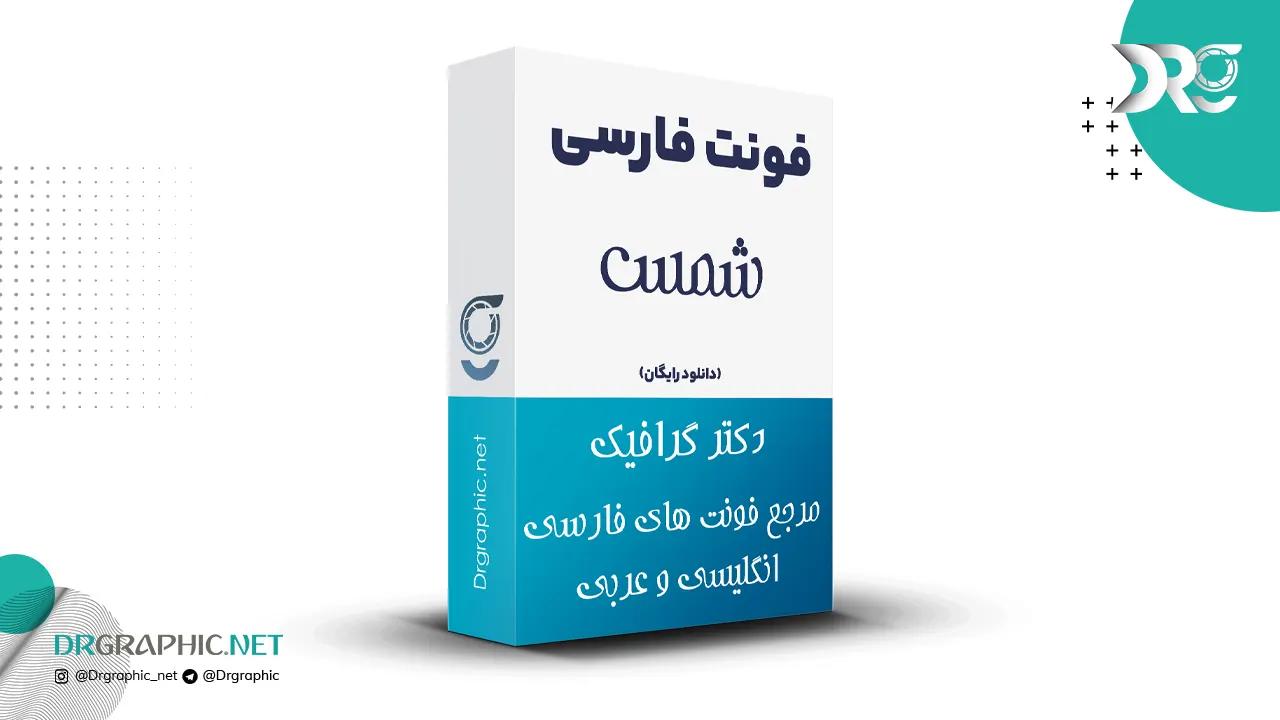
دانلود فونت فارسی شمس Shams
فونت شمس برای کاربردهای خاص طراحی و اجرا گردیده و برای استفاده طولانی در متن کاربرد ندارد. در طراحی این فونت سعی شده برخلاف قواعد فونت فارسی، اکثر حروف در بالای خط کرسی و مابین دو خط قرار می گیرند که همین امر موجب زیبایی و متفاوت بودن آن گردیده است.
این فونت در سال 1393 توسط محمدرضا شمس الکتابی طراحی و برای استفاده عموم به صورت کاملا رایگان برای دانلود گذاشته شده است. شما میتونید این فونت را از دکتر گرافیک دریافت کنید.
نمونه نوشته با این فونت: